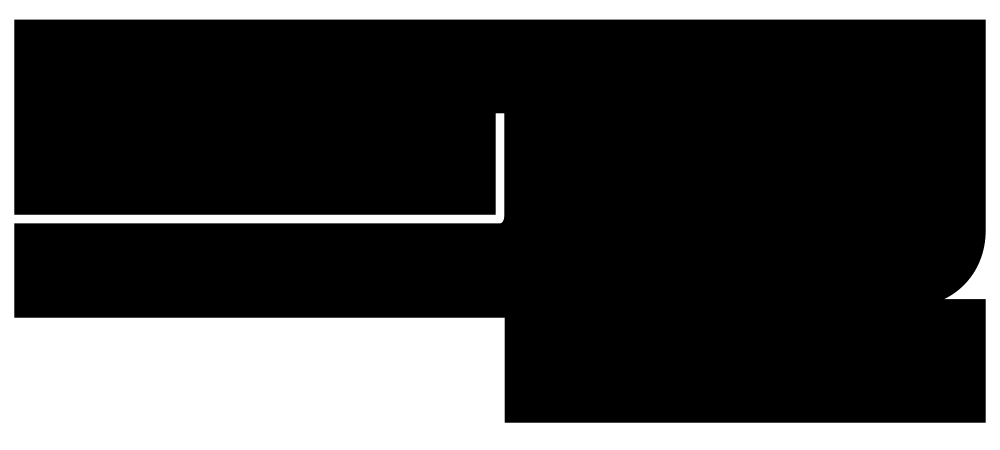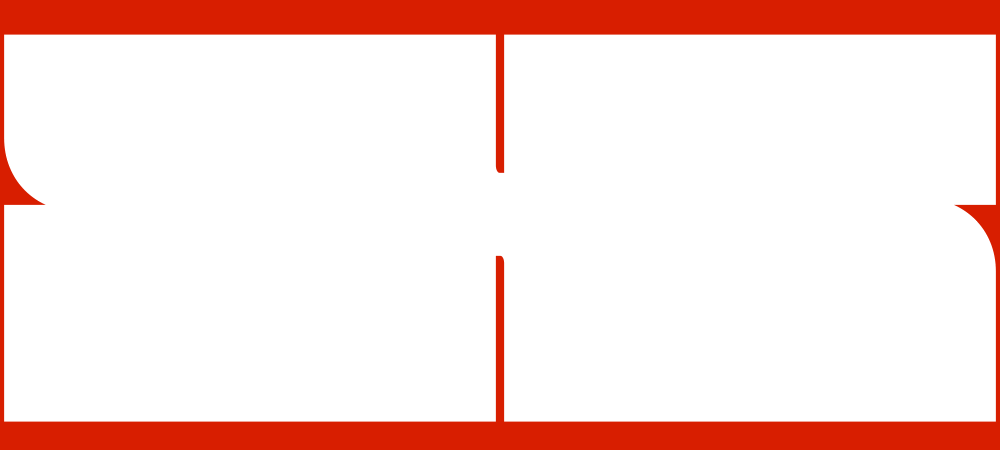
פיט עברית
NOW
FIT SUPPORTS
HEBREW
Fit at different widths; Thanks Lucas de Groot for the cool interpolation theory!
פיט הוא פונט דינמי (variable font) פורץ דרך, עם מטרה אחת: למלא מקסימום שטח. כל שטח.
לפונט פיט יש למעשה אינסוף משקלים - החל מהמשקל הצר ביותר (פיט סקייליין) ועד לרחב ביותר (פיט אולטרה אקסטנדד), המיוצגים כאן באופן סמלי על ידי עשרה משקלים. כל אות יכולה להמתח עד ל־3,600% כדי להגיע לרוחב המקסימלי. בין לבין תוכלו למצוא משפחה עשירה במשקלים שמתפקדים בכל כמות של טקסט או שטח.
הסוד נמצא בעיצוב החללים שבין האותיות: בלי קשר לרוחב, החלל בתוך האותיות והחלל בין האותיות נשאר זהה - מה שיוצר שטח טקסט מהפנט המורכב מקווים שחורים ולבנים.
Using Ross’s Latin version as a starting point, Ezer adapted Fit’s rigid design to suit the needs of the Hebrew alphabet. Taking into account the squareness of the letterforms and the direction in which they open, Ezer sensitively applied Fit’s system of alternating curves and corners. Just as Ross’s Latin mixes uppercase and lowercase forms to take up more space, Fit Hebrew seamlessly mixes block and cursive forms. Ezer pushes Fit’s Hebrew alphabet to surprising extremes, making it an unforgettable and adaptable tool for titling and poster work.